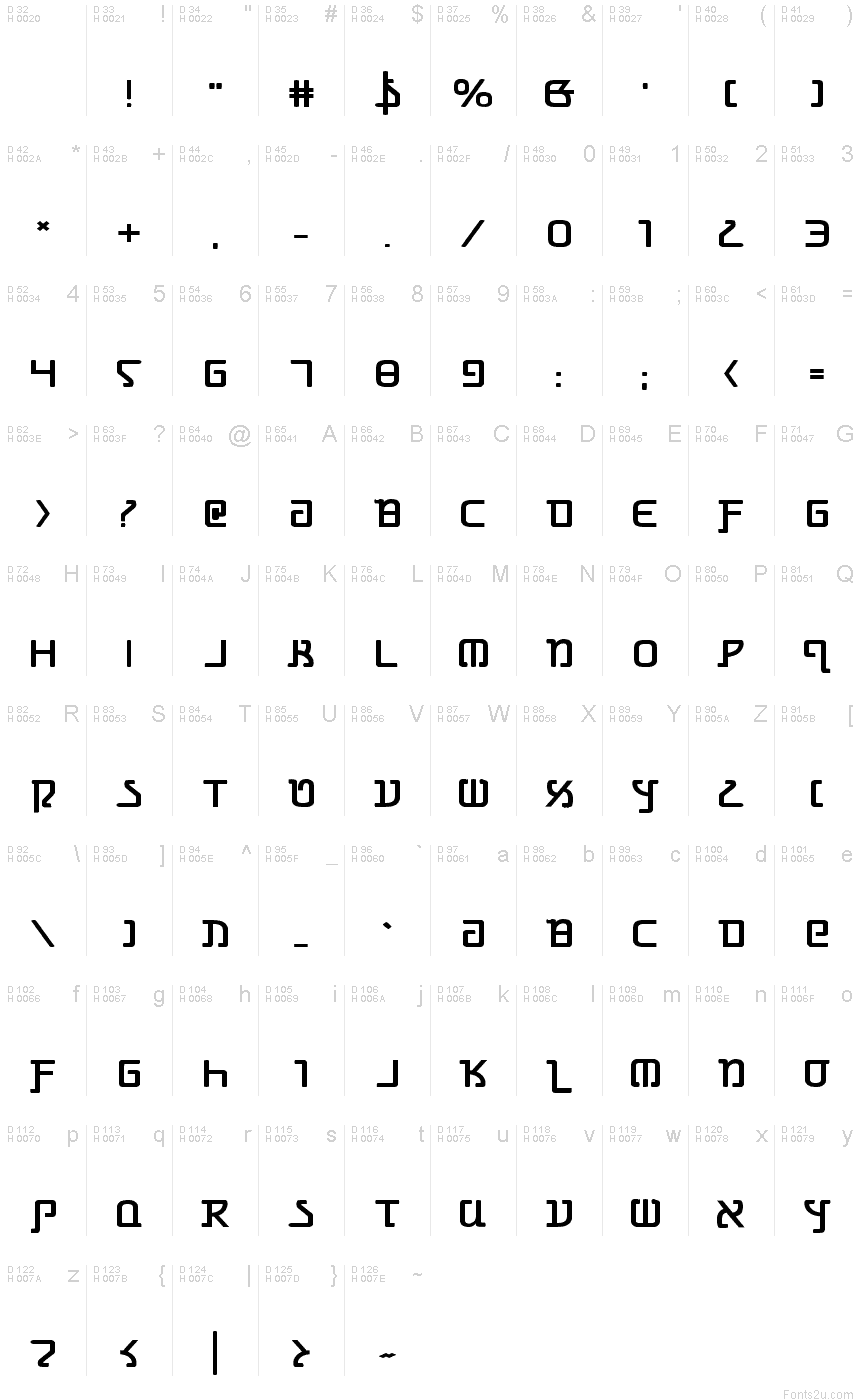
Grimlord Bold Expanded autorstwa Iconian Fonts to darmowy, retrofuturystyczny krój displayowy o szerokich, litych literach, zaokrąglonych zewnętrznych narożnikach i powtarzających się przerwach w pociągnięciach. Kwadratowe wewnętrzne cięcia nadają kształtom fabryczny, mechaniczny wygląd.
Interfejs gry science-fiction to jego najbardziej przekonujące środowisko, ponieważ szeroka konstrukcja wydaje się stworzona do ekranów sterowania i grafik frakcji. Ta sama industrialna geometria pasuje do plansz tytułowych filmów, brandingu technologicznego, gadżetów sportowych i plakatów muzyki elektronicznej. W otaczającej oprawie graficznej te przycięte szczeliny i segmentowane połączenia mogą przywodzić na myśl otwory wentylacyjne, układy elektroniczne lub obudowy maszyn, dzięki czemu liternictwo staje się częścią zaprojektowanego świata, a nie neutralnym podpisem.